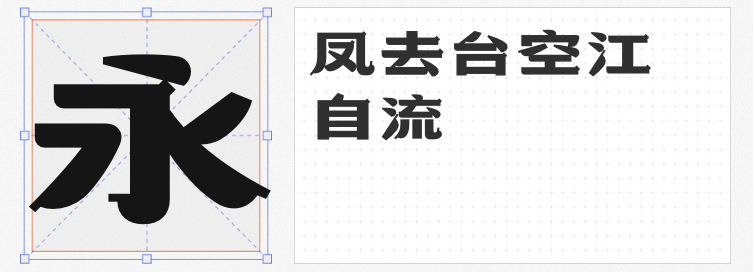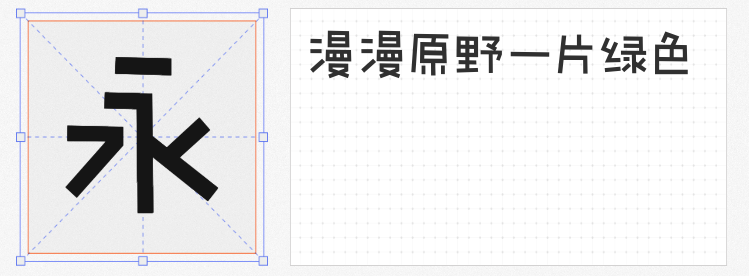
在电商视觉设计中,字体不仅是信息载体,更是品牌调性的直接表达。以下四款非免费商用字体凭借独特的设计语言,为电商场景注入活力与个性,助你轻松打造差异化视觉风格。
这款以手写感为基底的直线字体,通过“断开”笔画与去钩设计,打破传统字体的规整感。不同字型间细微的大小错落,赋予文字动态韵律,尤其适合母婴、潮玩类电商的标题设计。其灰度均匀的笔画组合,既能保证小字号的可读性,又能在大字号中展现几何美感,是营造清新治愈氛围的利器。
粗壮的方块字形与重心下移的设计,让这款字体自带“呆萌”属性。笔画转折处的钝感处理,搭配无衬线结构,形成类似积木拼接的视觉效果,完美契合宠物用品、儿童玩具等品类的“萌系”定位。在促销海报或产品详情页中,其笨拙可爱的形态能有效吸引年轻消费者注意力。
将圆形小球元素无规则嵌入字体结构,搭配拱形弧线笔画,这款字体以“曲直结合”的设计语言,精准捕捉Z世代对“调皮可爱”的审美偏好。无论是潮牌服饰的Slogan,还是二次元周边的标题设计,其不规则的元素分布都能强化品牌年轻化标签,提升视觉记忆点。
宽扁工整的字体骨架中,融入圆角起笔、方形折笔与切笔收尾等细节,形成“外柔内刚”的视觉张力。钩画外圆内方的设计,既保留传统宋体的书卷气,又通过几何化处理增强现代感。这款字体尤其适合茶饮、汉服等国潮品牌的包装设计,既能传递文化底蕴,又能以差异化字形脱颖而出。
电商设计的本质是“视觉说服”,而字体选择则是这场说服的底层逻辑。四款字体通过差异化的设计语言,为不同品类的电商场景提供了精准的视觉解决方案。在商业竞争中,善用字体设计的品牌,往往能以更低的成本,实现更高的视觉溢价。